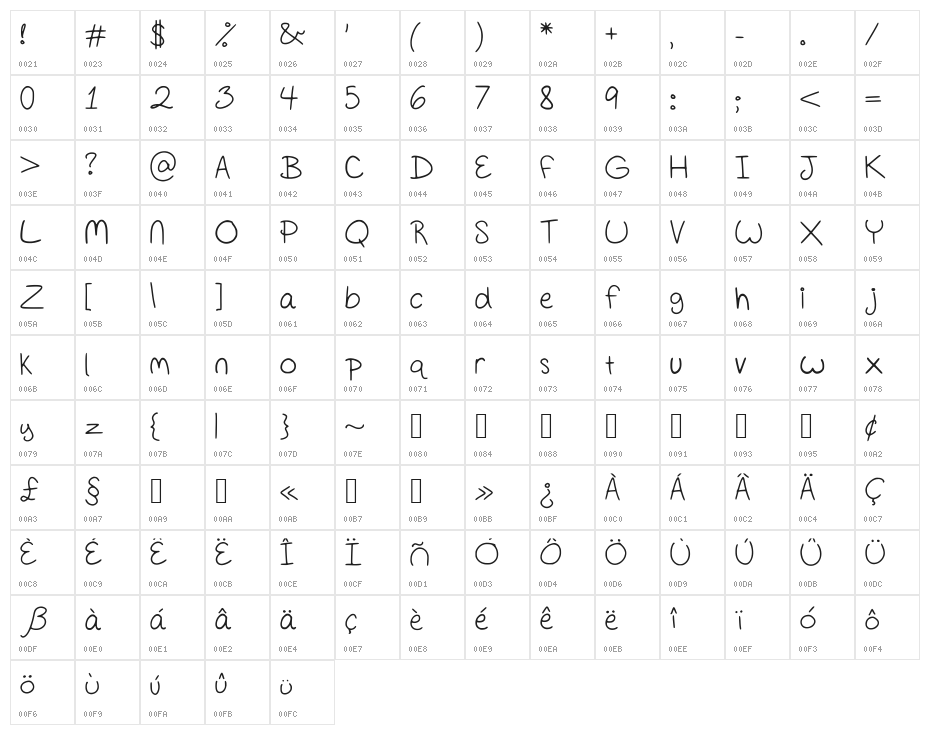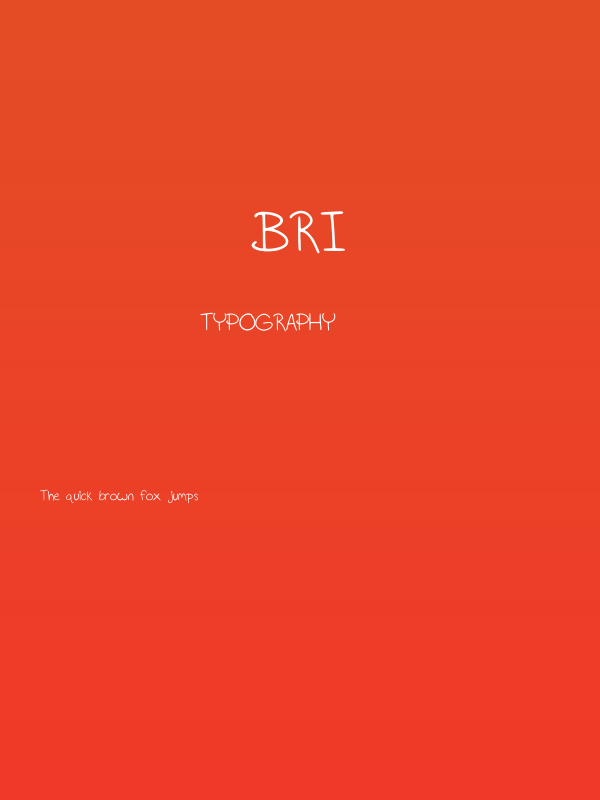
Bri Font
| Gesamtstil | Casual |
| Anwendungsfall | Headlines, Informal text, Branding |
| Vorgeschlagene Projekte | Ideal for children's books, greeting cards, informal invitations, and playful branding. |